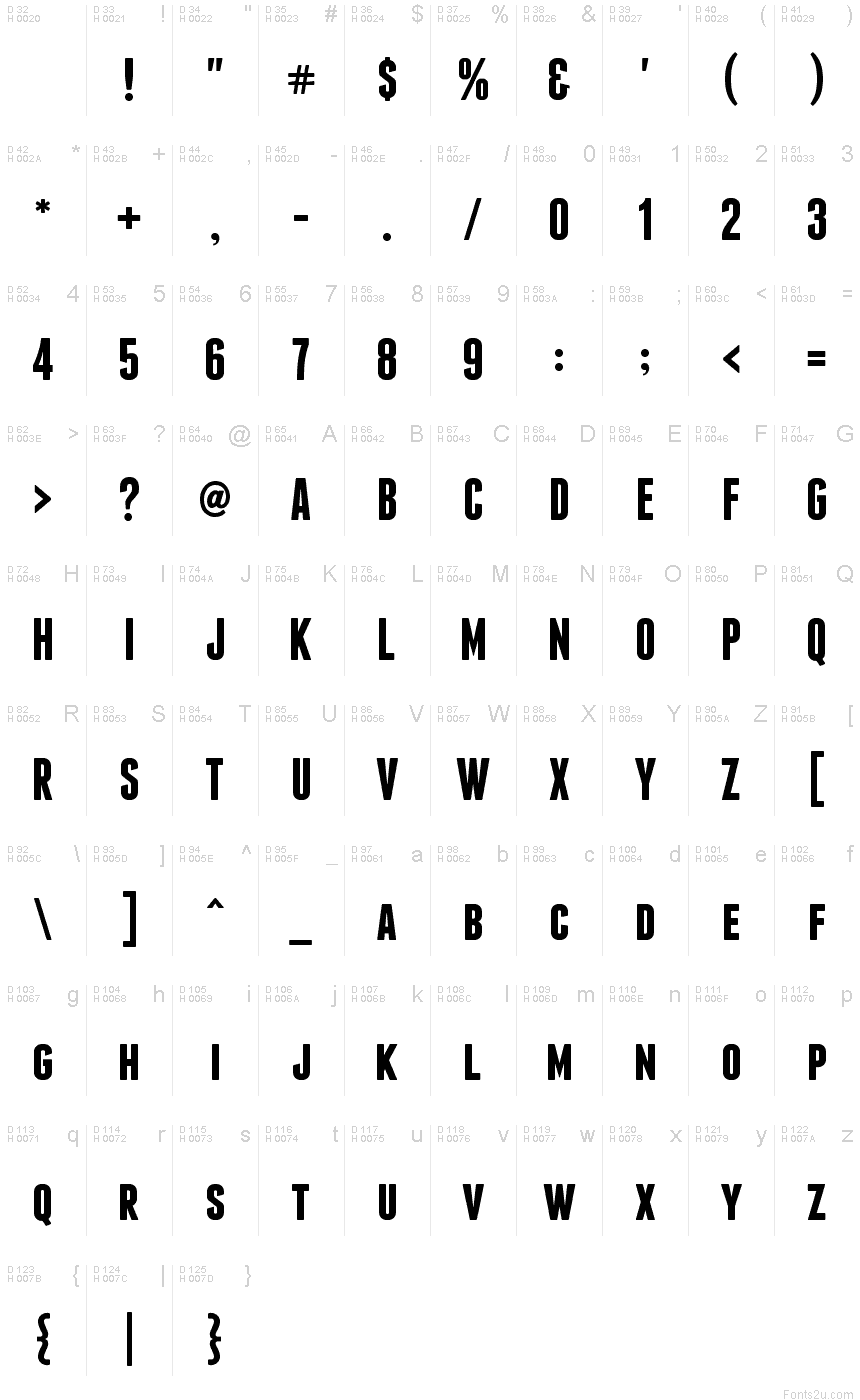
Franchise Bold ist eine kostenlose, schmale Serifenlose mit hohen, dicht beieinanderstehenden Großbuchstaben, harten, gerade abgeschnittenen Kanten und kleinen abgerundeten Partien, die verhindern, dass ihre strenge Kontur völlig rein geometrisch wirkt. Die Buchstaben wirken schmal, markant und zielgerichtet.
Das Branding von Sportteams ist ihr offensichtlichstes Zuhause, und die komprimierten Formen eignen sich auch für Stadionbeschilderungen, Sportbekleidung, Spielcover sowie Einzelhandelsverpackungen. Die gerade abgeschnittenen Oberseiten und langen, aufrechten Striche erinnern an gemalte Blockbuchstaben auf Anzeigetafeln, Trikotbeschriftungen und Industrieetiketten.
Franchise